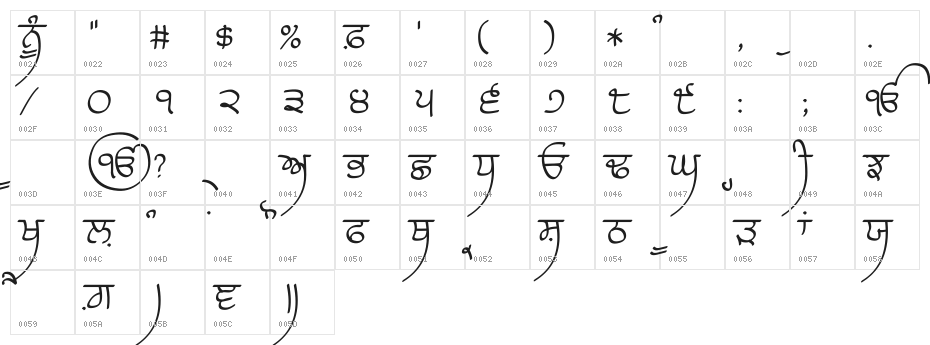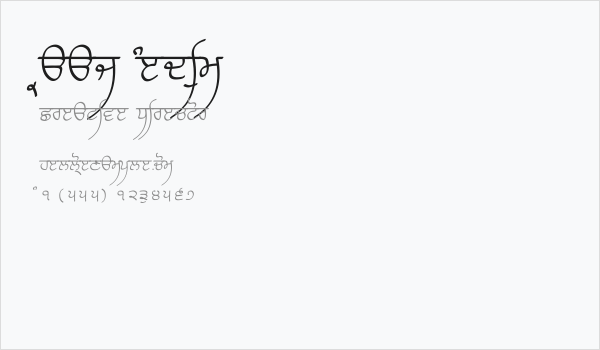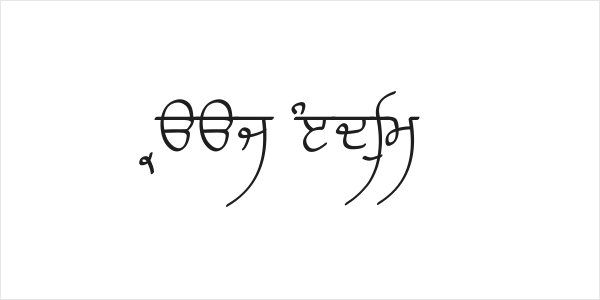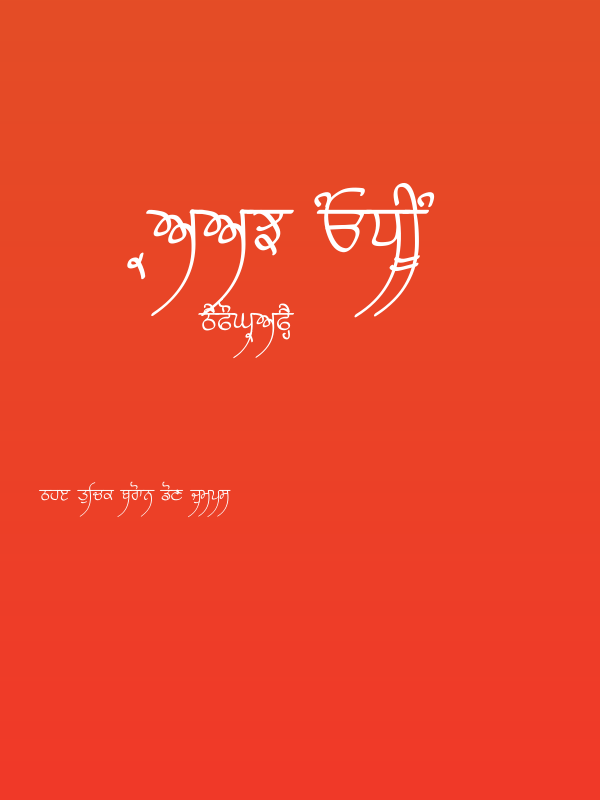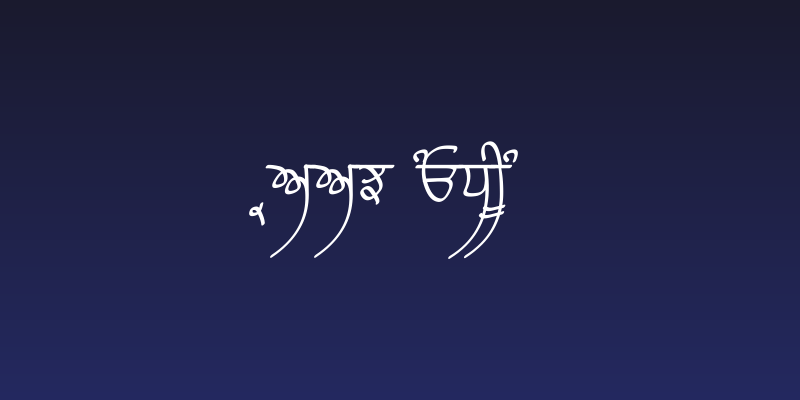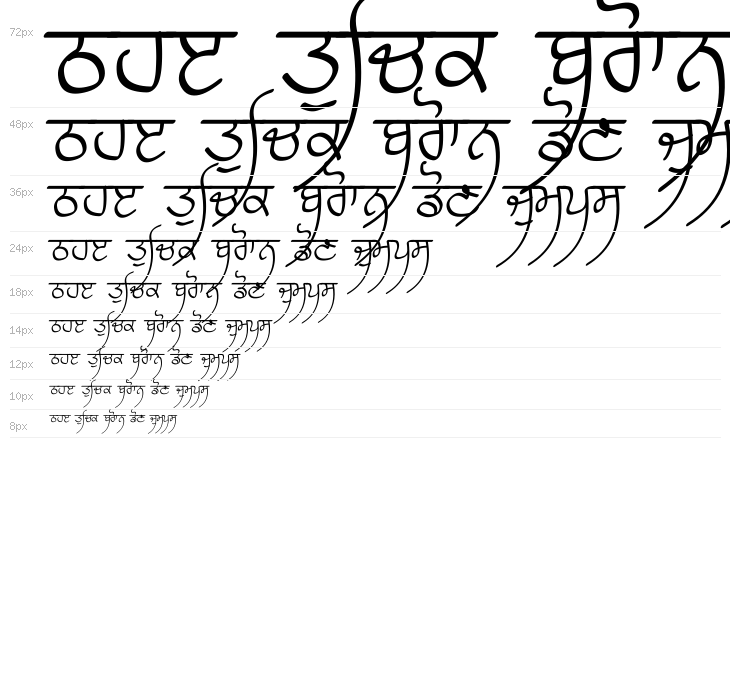
Raaj Medium Font
| Caso d'uso | Decorative, Formal documents |
| Progetti proposti | Ideal for wedding invitations, formal event programs, elegant branding, and decorative print materials. |